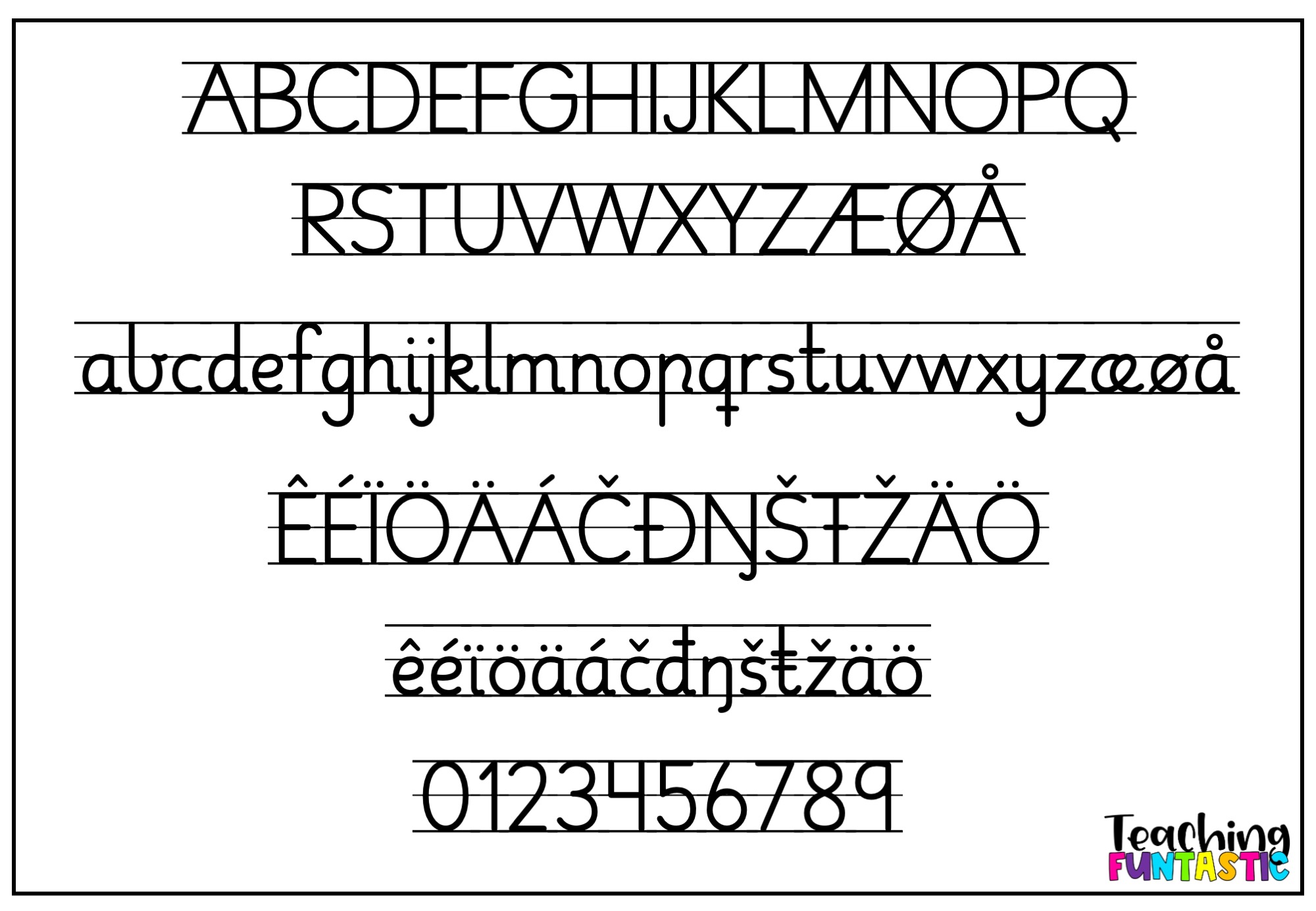
FUNtastic Trykkskrift 2 Bokstavhus – en font til trening av håndskrift
Funtastic Trykkskrift 2 – Bokstavhus er en linjert versjon av FUNtastic Trykkskrift 2, der bokstavene automatisk plasseres i et ferdig bokstavhus med hjelpelinjer. Perfekt til oppgaveark, skriveøvinger og bokstavforming i begynneropplæringen!
Denne fonten gjør det enkelt å lage skrivetreningsark uten behov for å sette inn linjer selv – bare skriv rett i Word eller PowerPoint, så vises bokstavene med riktige linjer, som et bokstavhus.
I denne fonten har bokstavene “hale”, og åpen b og p, slik at det blir enklere for elevene å binde sammen bokstavene senere.
Perfekt for skrivetrening i begynneropplæringen
Når barn lærer å skrive, er det viktig at de øver med tydelige, gjenkjennelige bokstavformer. Med denne fonten kan læreren raskt lage tilpassede oppgaver som bokstavark og skriveøvelser. Elevene får øve både motorisk og visuelt, med bokstavformene de ellers lærer å lese og skrive. Det gir trygghet og mestring i skriveprosessen – spesielt for elever som trenger mer støtte i finmotorikk og bokstavenes plassering.
En font håndskrift laget for lærere
FUNtastic Trykkskrift 2 Bokstavhus er enkel å installere og bruke i PowerPoint, Word eller Canva Pro. Den gir deg full frihet til å designe oppgaver som passer akkurat din klasse. Fonten er utviklet som lesbar font for barn, og passer perfekt til alt fra bokstavforming og finskrift til skrivetrening.
Norsk font med alle bokstaver
Fonten inkluderer alle de norske og samiske bokstavene. Bokstavene har balansert høyde og avstand for best mulig lesbarhet, både på skjerm og utskrift.